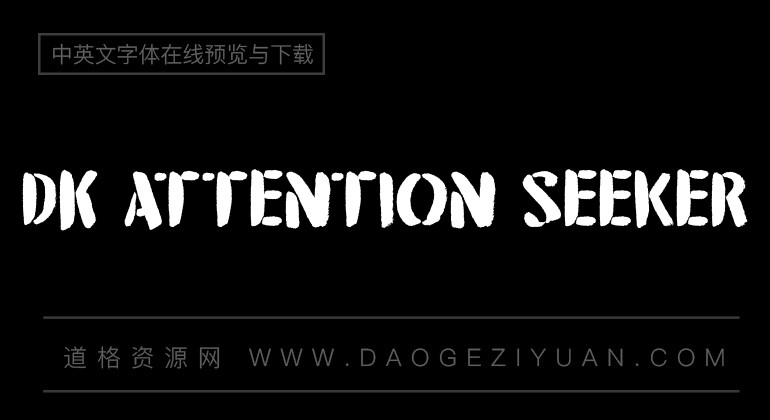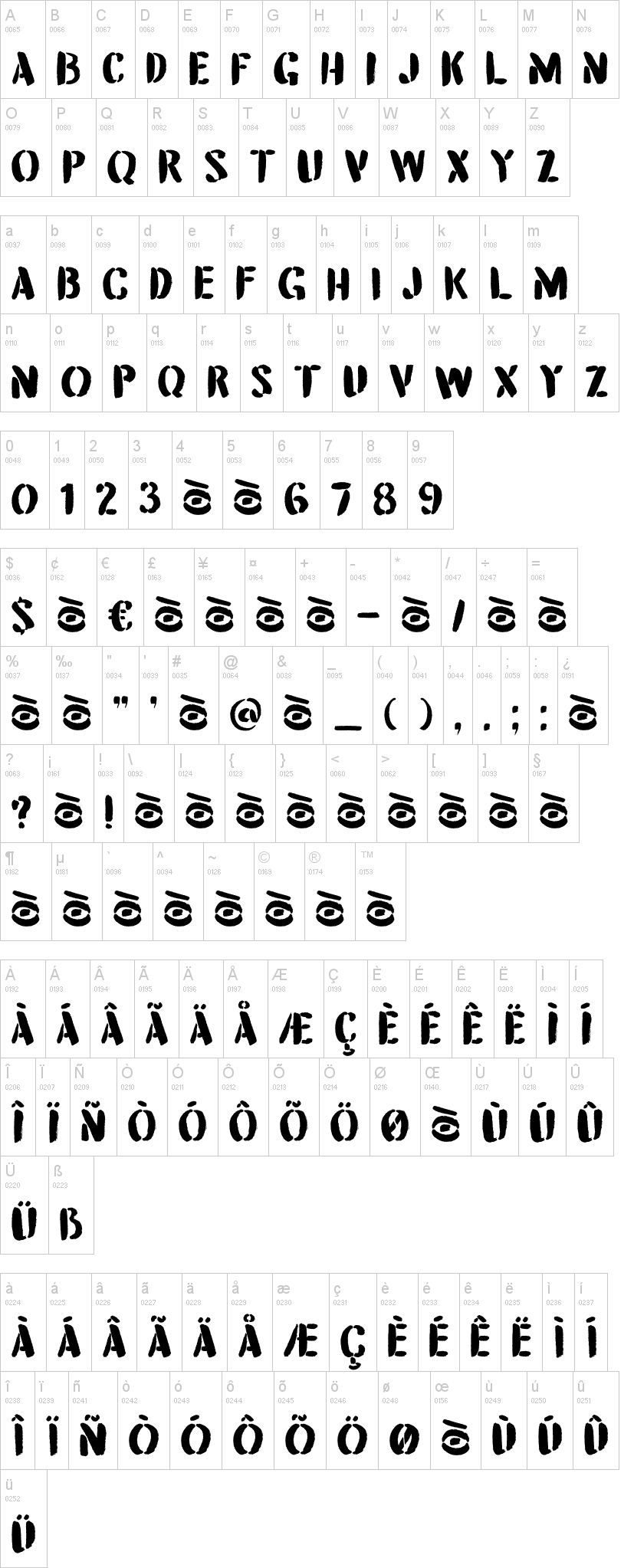
DK Attention Seeker 是一款具有强烈引人注目效果的字体,它采用粗体、细体和粗体细体结合的设计,使文字更加醒目。它的字形具有清晰的轮廓,细节处理精细,具有复古时尚的外观,适用于各种类型的品牌标识、海报、广告等。内容介绍
DK Attention Seeker是一款非常不错的手写艺术字体,具有很好的视觉感,适合于文化类的宣传设计、商业类品牌的广告和产品包装设计以及个性化文字排版等较多场景。